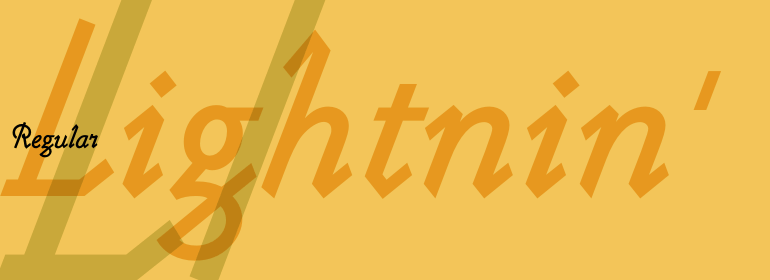
Lightnin'™
Lightnin'™,这款字体结构工整、笔画清晰,兼顾美观与易读性,适用于标题、正文、海报、包装、LOGO 等多种场景。字形优雅稳定,风格百搭耐看,适配日常排版与创意设计,让文字呈现更舒适、更具质感。Lightnin'™一笔一画,皆是细节,以均衡的比例、流畅的线条打造舒适视觉体验,字形端正大气,风格简约现代。无论是商业设计、品牌宣传还是日常排版,都能轻松驾驭,让文字更有格调与力量。Lightnin'™字体下载。
字体品牌: ITC(Monotype) 设计师:Meeks,Alan 字体分类:书法体 字体属性:外文 字符集:Unicode 发布时间: 2018